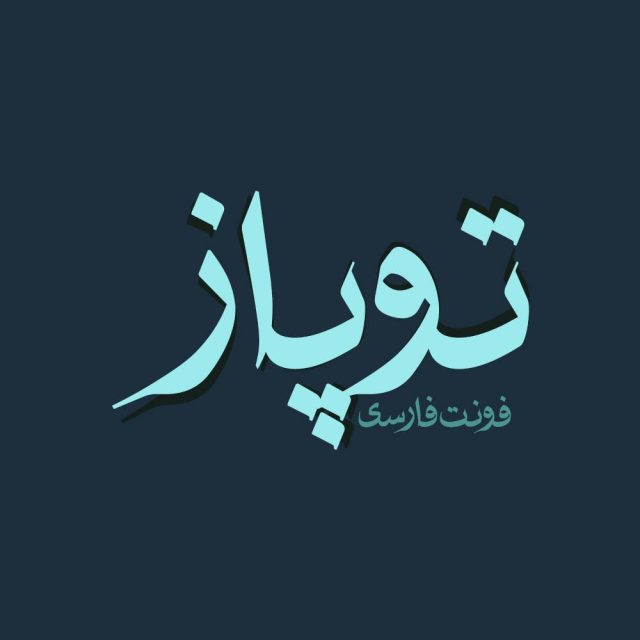
فونت فارسی توپاز Topaz Font
فونت فارسی توپاز با دقت فنی بالا، طراحی زیبا، و کیفیت بینظیری طراحی و منتشر شده است. فونت توپاز به عنوان ابزار برجسته شما را در…
فونت فارسی توپاز با دقت فنی بالا، طراحی زیبا، و کیفیت بینظیری طراحی و منتشر شده است. فونت توپاز به عنوان ابزار برجسته شما را در ارتقاء حرفهای نمایش محتوای فارسی در وب و چاپ کمک خواهد کرد، فونت فارسی توپاز در دسته فونتهای نسخ نمایشی قرار دارد که برای طراحیهای خلاق و متنهای کوتاه بسیار مناسب است.
پیشنمایش و نمونه تایپ های فونت توپاز